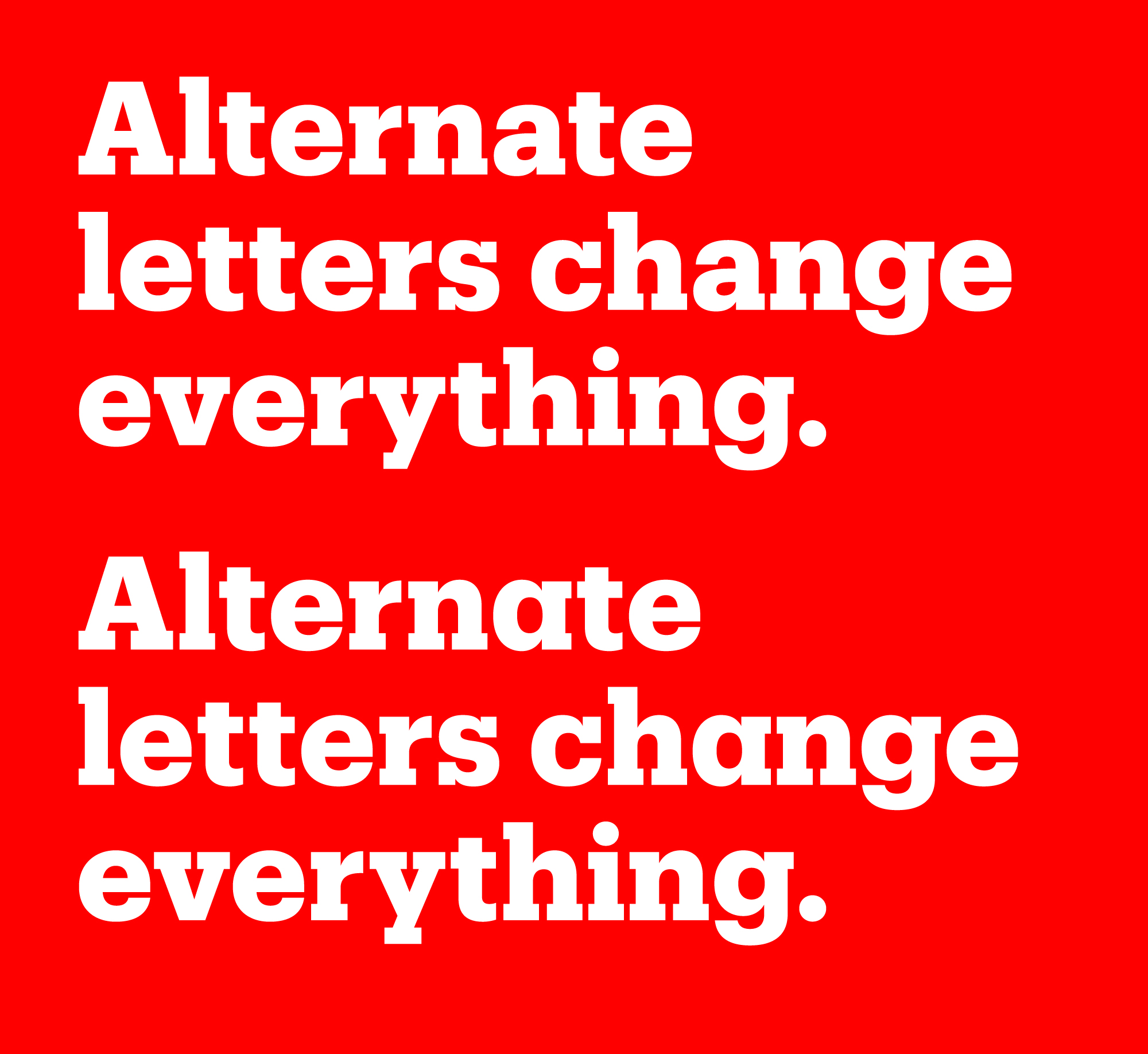
Новый шрифт: Produkt
Современная брусковая антиква, нарисованная, чтобы работать в паре с Graphik
Produkt — универсальная брусковая родственница шрифта Graphik. У Produkt — те же низкий контраст, компактные пропорции, небольшая разница в высоте между прописными и строчными и та же палитра начертаний (девять вариантов насыщенности с курсивом для каждого). Всё это дополнено аккуратными и достаточно короткими (особенно в жирных начертаниях) засечками. Produkt подойдёт для акциденции, мелких кеглей и узких утилитарных задач (например, для навигации и картографии).
Автор Produkt — Бёртон Хасебе — выпускник Колледжа искусств и дизайна в Лос-Анджелесе и курса TypeMedia в KABK. С 2008 по 2013 год работал штатным дизайнером в Commercial Type, а после — основал собственную студию. В каталоге type.today есть и другие шрифты Бёртона — Druk, Platform и Styrene. Кириллицу Product сделали в студии CSTM Fonts.